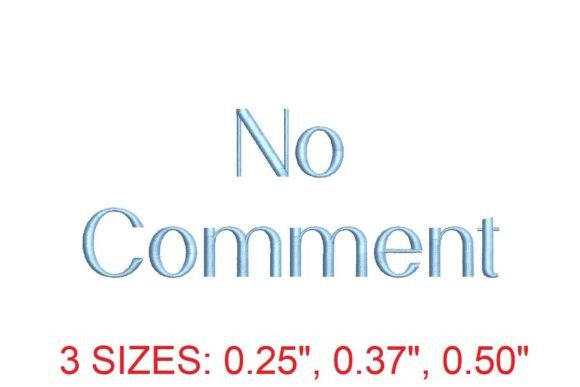
No Comment Embroidery Font
Encontrar los elementos de diseño adecuados puede ser un desafío, pero No Comment Embroidery Font ofrece una colección excepcional que eleva tu trabajo al instante.